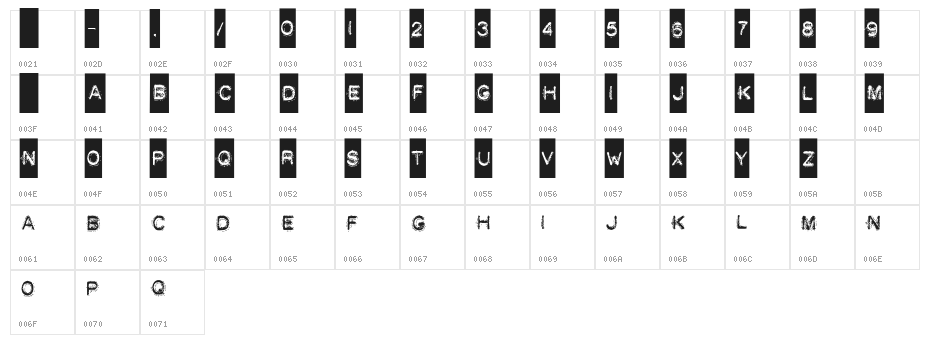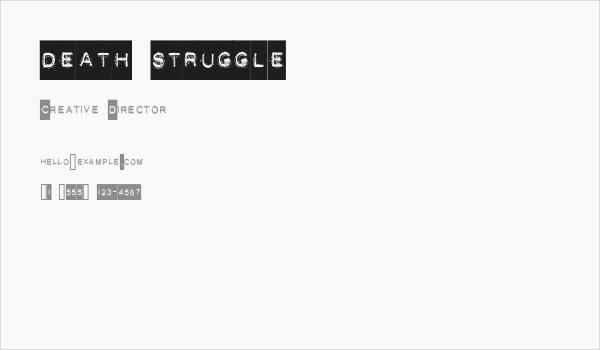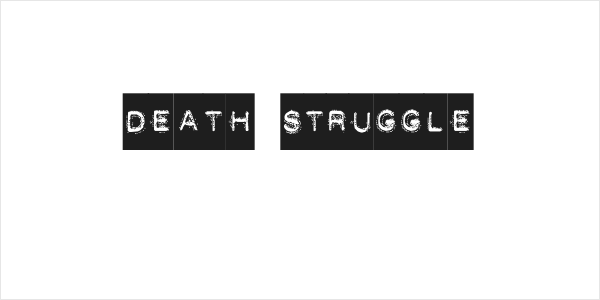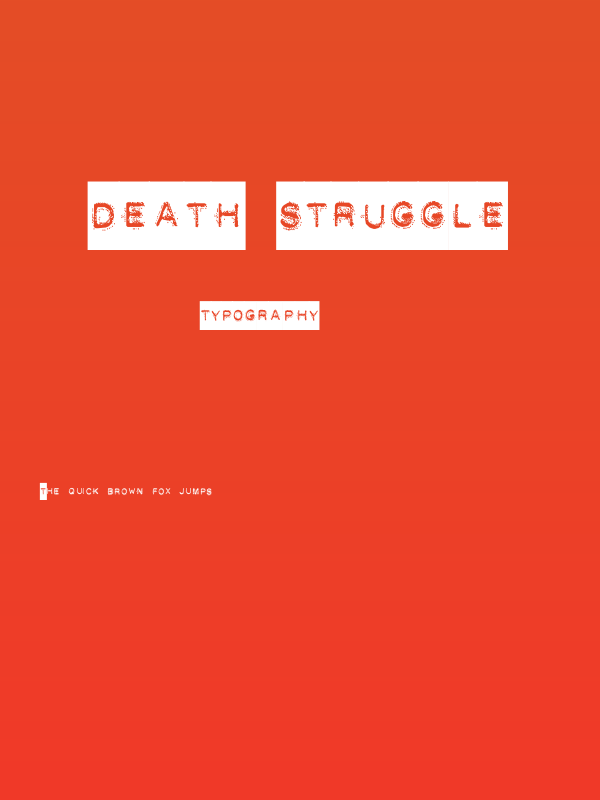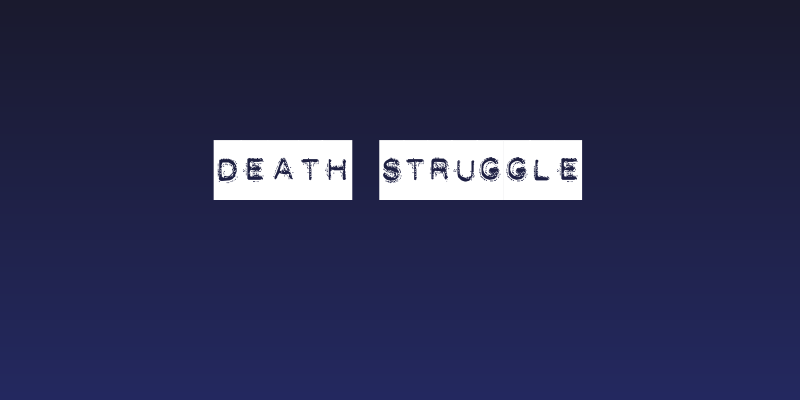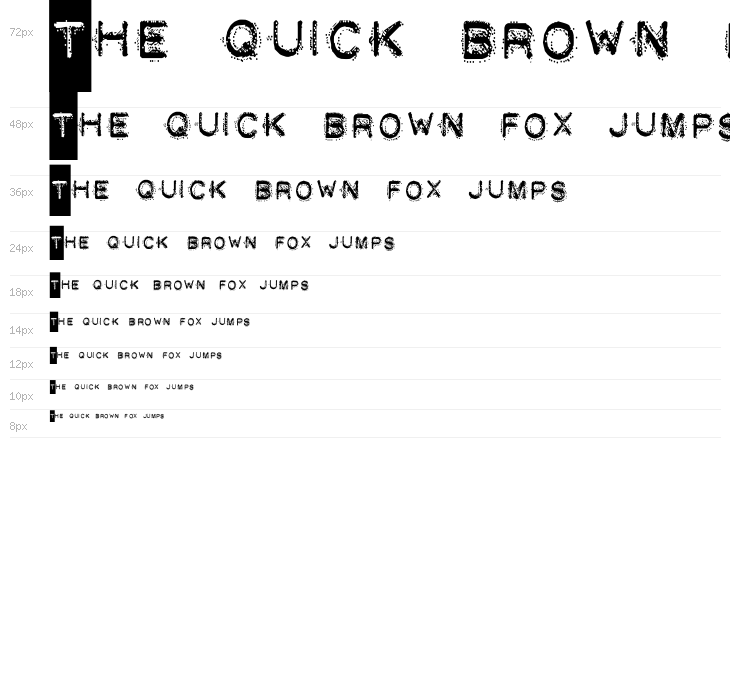
DEATH STRUGGLE Font
| Stil general | Vintage, Grunge |
| Proiecte propuse | Ideal for music album covers, edgy posters, alternative branding, and punk-themed events. |